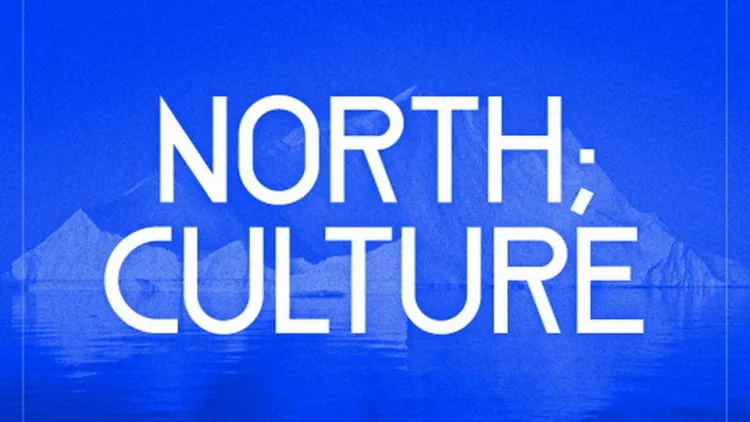
Esta é uma elegante e versátil fonte sans-serif. Ela foi criada por Felipe Elioenay e compartilhada pela 99designs. Esta é uma tipografia geométrica moderna com uma aparência limpa e poderosa. A família da fonte inclui três estilos: Regular, Ultra Light e Inline. Estas opções de estilo permitem que você personalize sua experiência visual, adaptando-a ao seu próprio gosto ou ao design específico do projeto. Seja para anúncios digitais, designs gráficos ou qualquer formato digital que precise de uma fonte robusta e sofisticada, esta família de fontes é perfeita. Especialmente adequada para ambientes modernos e tecnológicos, a North Culture Font Family oferece um equilíbrio entre simplicidade e força visual. Ela se destaca em qualquer formato, seja em headlines poderosas ou textos leves que requerem legibilidade e simplicidade. Essas características combinadas resultam numa fonte perfeita para qualquer projeto digital contemporâneo. Seja para criar um site web dinâmico, desenvolver uma identidade visual única ou até mesmo personalizar documentos de trabalho, a North Culture Font Family é uma escolha inteligente que certamente complementará o seu design.